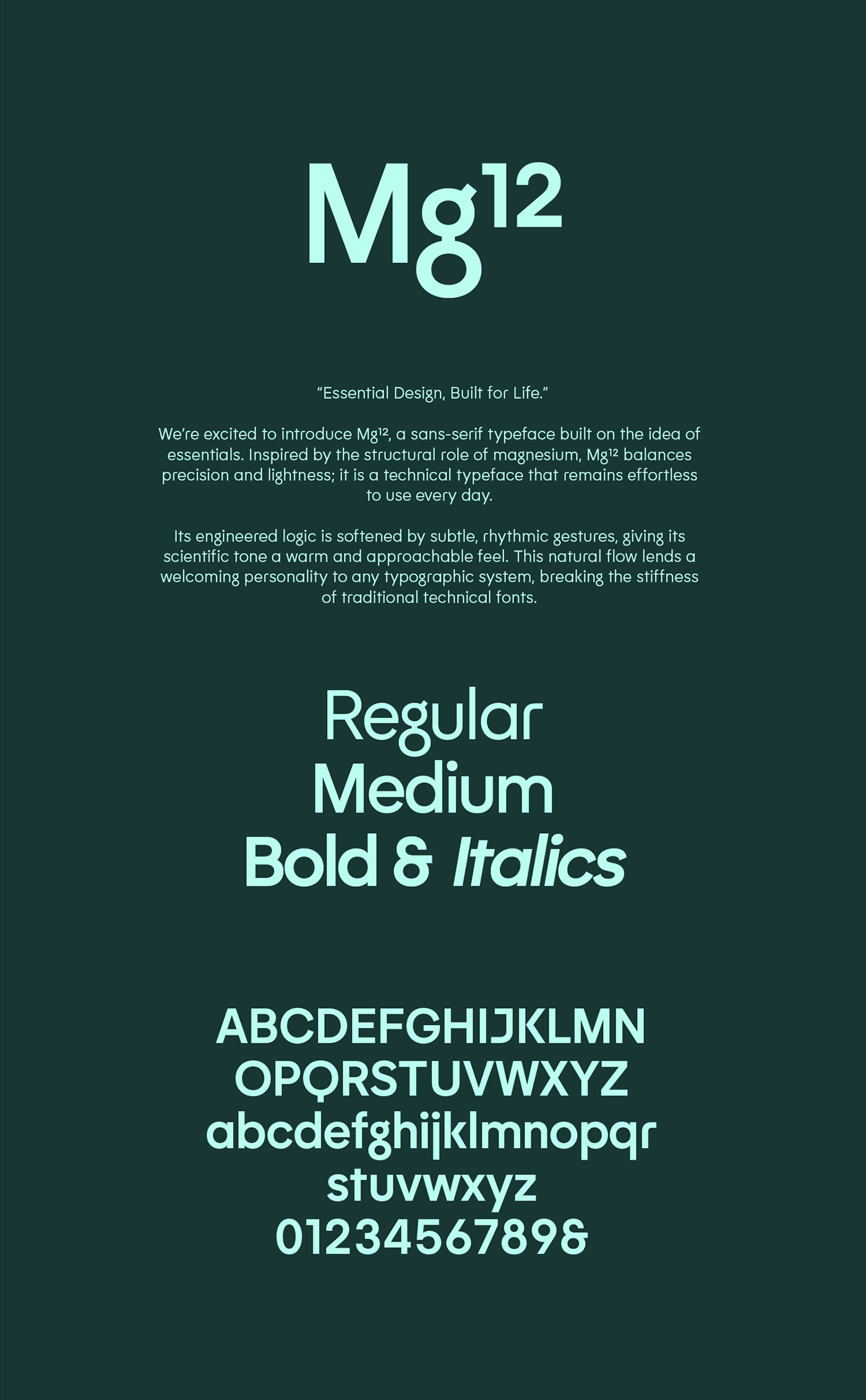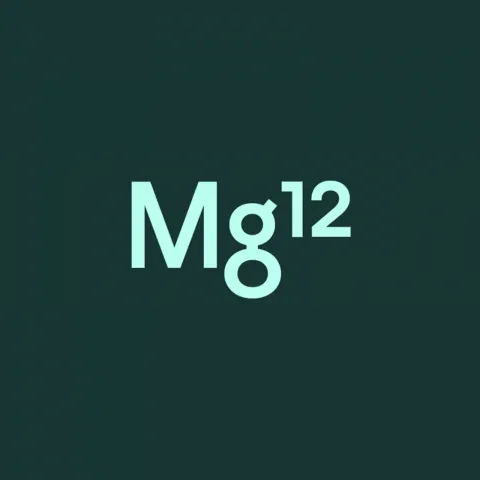
atipo ® vừa chính thức trình làng Mg¹², một bộ font sans serif đề cao tính công năng, được xây dựng dựa trên vẻ đẹp hình học và các nguyên lý thiết kế tối giản dành riêng cho các dự án branding.
Được thiết kế bởi studio atipo ® từ Tây Ban Nha, Mg¹² là sự giao thoa mượt mà giữa độ chính xác kỹ thuật và những chi tiết nhịp điệu đầy tinh tế. Lấy cảm hứng từ cấu trúc của nguyên tố magnesium, bộ font này đóng vai trò như một nền tảng vững chắc cho các thiết kế nhận diện thương hiệu. Với diện mạo thanh thoát, Mg¹² mang đến một hệ thống phân cấp thị giác (visual hierarchy) mới mẻ, giúp các ứng dụng branding tránh được sự khô cứng thường thấy ở các kiểu chữ kỹ thuật truyền thống.
Điểm khác biệt của Mg¹² so với các font kỹ thuật thông thường chính là những đường cong mềm mại và hình khối dễ chịu hơn hẳn. Bộ font này cung cấp 6 độ dày (weights) khác nhau, từ Thin cho đến Bold, hỗ trợ các designer tạo nên những layout dễ đọc và thoáng đãng mà không bị rối mắt. Chính dòng chảy tự nhiên này đã tạo nên cá tính riêng cho các thiết kế dàn trang (editorial design), nhận diện doanh nghiệp hay hệ thống biển chỉ dẫn.